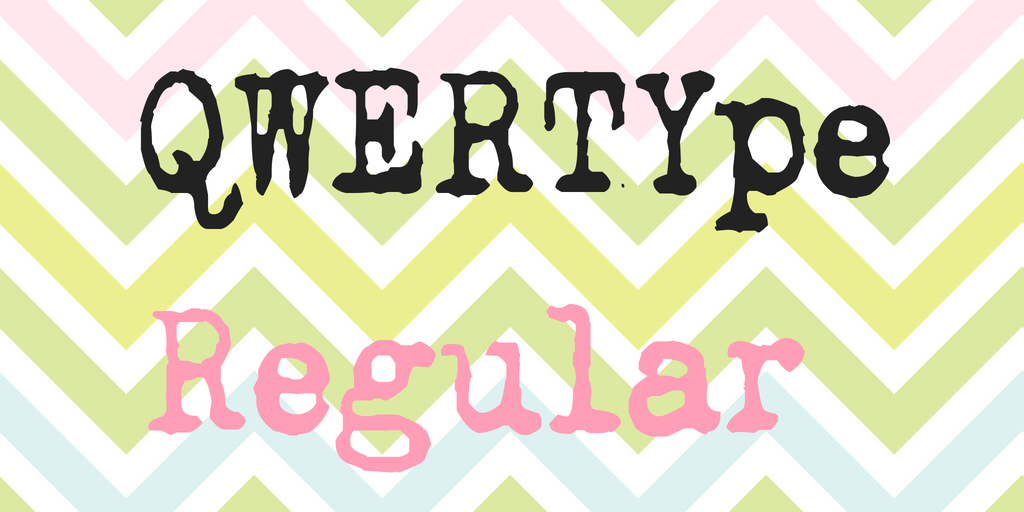
QWERTYpe Font
Aqui está uma versão em português do Brasil para a descrição da página de download da font ‘QWERTYpe Font’: Estamos muito felizes por você ter escolhido nosso QWERTYpe Font para seu próximo projeto! Este é um conjunto de fontes serif livres, criado pelo talentoso designer Hamilton. As fontes serif são conhecidas por suas linhas mais finas e detalhes em sua tipografia que muitos dizem dar um tom mais formal às letras. A fonte QWERTYpe foi projetada para oferecer uma textura elegante que combina bem em design gráfico, sites, ou até mesmo como parte de seu branding. Se você está interessado em usá-la em um projeto comercial, pode adquirir a licença com uma contribuição simples de 15€ ($20) por meio do PayPal. Para ajudar a contribuir para nossas fontes gratuitas e livres de uso, oferecemos um botão de doação. Você também pode usar o botão de download direto embaixo deste texto como uma maneira de adquirir sua licença. Não importa se você é um artista digital ou designer gráfico iniciante ou profissional, nosso QWERTYpe Font certamente terá seu lugar no seu arsenal de fontes. Esperamos que você adorará criar trabalhos incríveis com o QWERTYpe Font.